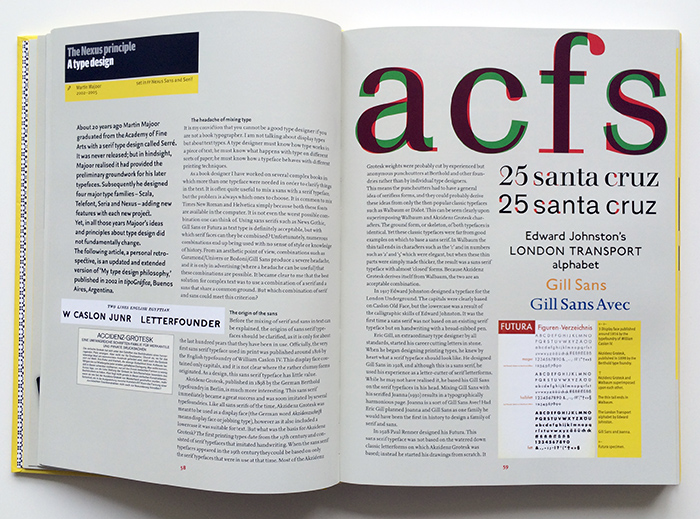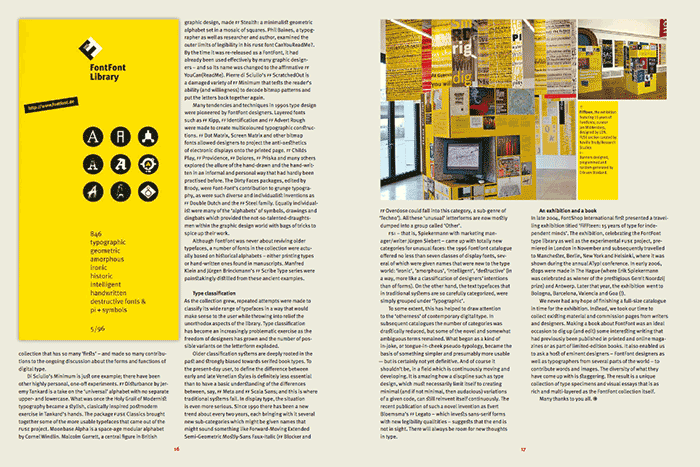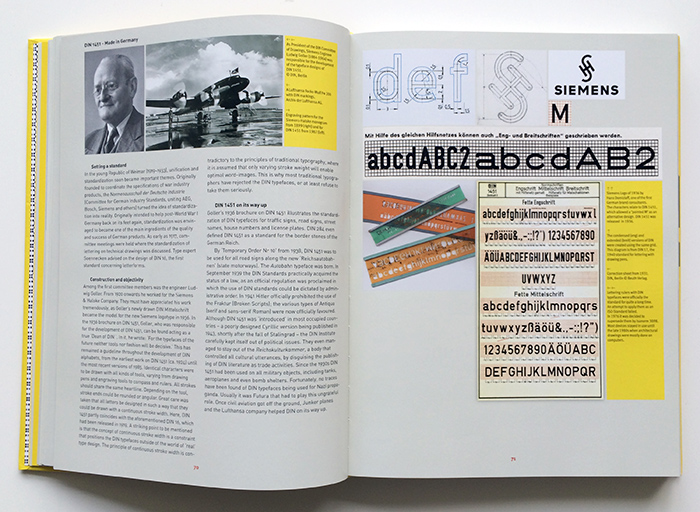
Die FontFont-Bibliothek wurde 1990 von Erik Spiekermann und Neville Brody gegründet und entwickelte sich rasch zu einem der führenden Anbieter für zeitgemäße Schriftgestaltungen. Das englischsprachige Buch Made with FontFont erzählt die Geschichte der Foundry, ihrer Designer und insbesondere ihrer Schriften.
Den ersten Teil des Buches machen Essays aus:
- Post Mortem, pre-Meta. Erik Spiekermann
- Is Best really Better? Erik van Blokland and Just van Rossum
- LettError. Emily King
- Type, Geometry, Construction. Jan Middendorp
- Max Kisman. Emily King
- FF Quadraat: Legibility, versatility, flamboyance. Fred Smeijers
- Infographics. Erik Spiekermann
- The Nexus Principle. Martin Majoor
- FF DIN, history of a contemporary typeface. Albert-Jan Pool
- Søndergaard, Olsen and the Danish lettering tradition. Jan Middendorp
- Evert Bloemsma. Jan Middendorp
- The Glasgow typeface. Patrick Baglee
- Grandmother’s bitmaps, FF Nelio. Jan Middendorp
- FF Profile. Warm-hearted Modernism. John Berry
- FF Clifford. Akira Kobayashi
- FF Clifford specimen.Piet Schreuders
- FF Danubia. Brigitte Willinger
- The record-breaking Fago. Antje Dohmann
- Form metal to Postscript: Berlow revives Bernhard. Jürgen Siebert
- Made for magazines: FF Zine. Antje Dohmann
- GF Bau: More than a revival. Christian Schwartz
Im nächsten Kapitel (Making FontFont) geben FontFont-Designer Einblick in ihre Arbeit und erklären ihre Schriftgestaltungen:
- FF CST Berlin East & West. Verena Gerlach
- A Brief History of FF Fontesque. Nick Shinn
- FF Strade, a multilingual sans-serif. Albert Pinggera
- FF Karbid. Verena Gerlach
- From a to a. Martin Wenzel
- Beekman’s alphabets. Donald Beekman, Jan Middendorp
- Handwriter & a lot of other beautiful type faces. Alessio Leonardi
- Basic ingredients. Stephan Müller
- Eboy Fonts. FF Beadmap. FF Caronnage. FF Klunder. FF Pepe FF Masterpiece
Im anschließenden, größten Teils des Buches werden dann Schriften der FontFont-Bibliothek in ihren Schriftmuster-Darstellungen präsentiert.
- FF Scala
- FF Nexus
- FF Meta
- FF Blur
- FF Oneleigh
- FF Eureka
- FF Magda
- FF DuDuchampp
- FF Legato
- FF Parango/FF Trombo
- FF Sheriff
- FF Hydra
- FF Angkoon
- FF Absara
- FF Market
- FF Jacky/FF Beadmap/FF Extra/FF Instanter
- FF Prater
- FF Letter Gothic/FF Letter Gothic Slang
- FF Archian
- FF Lancé Condensed
- Cyrillic FontFonts
- FF Roice
- FF Fago
- FF Quadrat
- FF Isonorm
- FF Unit
- FF Acanthus
- FF Cellino
- FF Danubia
- FF Balance/FF Tronic
- FF Maiola
Einerseits fungiert das Buch natürlich als werblicher Schriftmusterkatalog, der im Gegensatz zu Webseiten zum bequemen Schmökern auf der Couch einlädt. Die teils umfangreichen Hintergrundinformationen und Essays machen das Buch aber auch als Fachbuch interessant. Insbesondere auch deshalb, da die bekanntesten Schriften der FontFont-Bibliothek stilprägend für das Grafikdesign der letzten 20 Jahre waren.